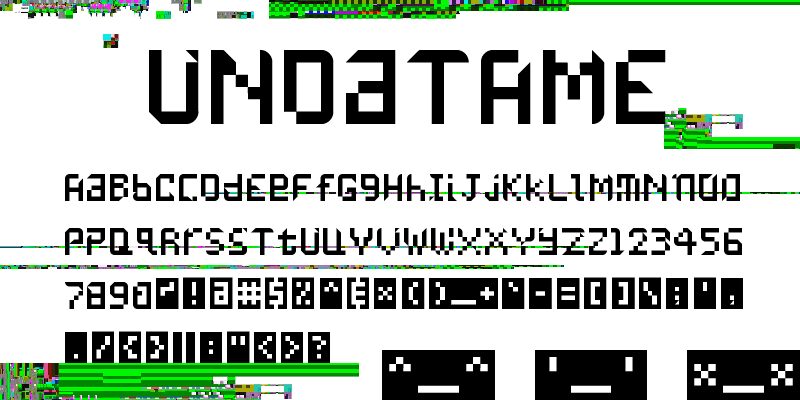
Undatame von Vaughn Royko ist eine kostenlose, futuristische Schablonenschrift, die aus breiten quadratischen Formen, präzisen geometrischen Verbindungen und starren Proportionen aufgebaut ist. Diagonale Schnitte verleihen den massiven Großbuchstaben einen maschinell bearbeiteten Look.
Ihr digitaler Sci-Fi-Stil eignet sich für Spieloberflächen, Cover elektronischer Musik und Grafiken für Technologie-Events. Die wiederkehrenden Aussparungen können an Leiterbahnen oder segmentierte Displayanzeigen erinnern, wodurch die Schrift zu einem Teil der Benutzeroberfläche statt zu einer neutralen Beschriftung wird.